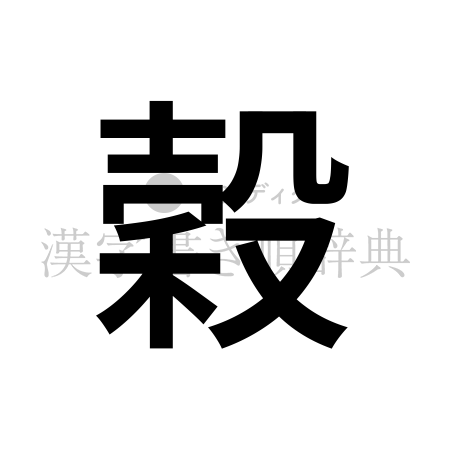
漢字「穀」(コク)の書き順・読み方・意味・部首・画数
「穀」の意味
- 穀物の総称。
- 食用となる植物の種子。
- 五穀(米、麦、粟、豆、黍)のこと。
- 穀物を育てること。
- 穀物を収穫すること。
「穀」の意味の英訳
漢字は1文字で多様な意味を持ちますが、「穀」を英語で表す場合、一般的には cereals, grain などがあります。
「穀」の成り立ち・由来
| 構造 | 意符「禾」+音符「㱿(こく)」 |
「穀」は形声文字です。作物・穀類に関わることを表す意符の「禾(のぎ・穀物)」と、音を表す音符「㱿(こく)」とを組み合わせて成り立ちました。「㱿」は、外側を殻でつつむような意味合いをもつ音符で、殻におおわれた実、すなわち食用となる植物の種子を示します。ここから、米・麦・粟・豆・黍などの穀物の総称を表す字となりました。旧字体「穀」の複雑な字形が、そのまま常用の字体として受け継がれています。
- 穀倉 - こくぐら
- 穀物をたくわえておく倉。こくそう。